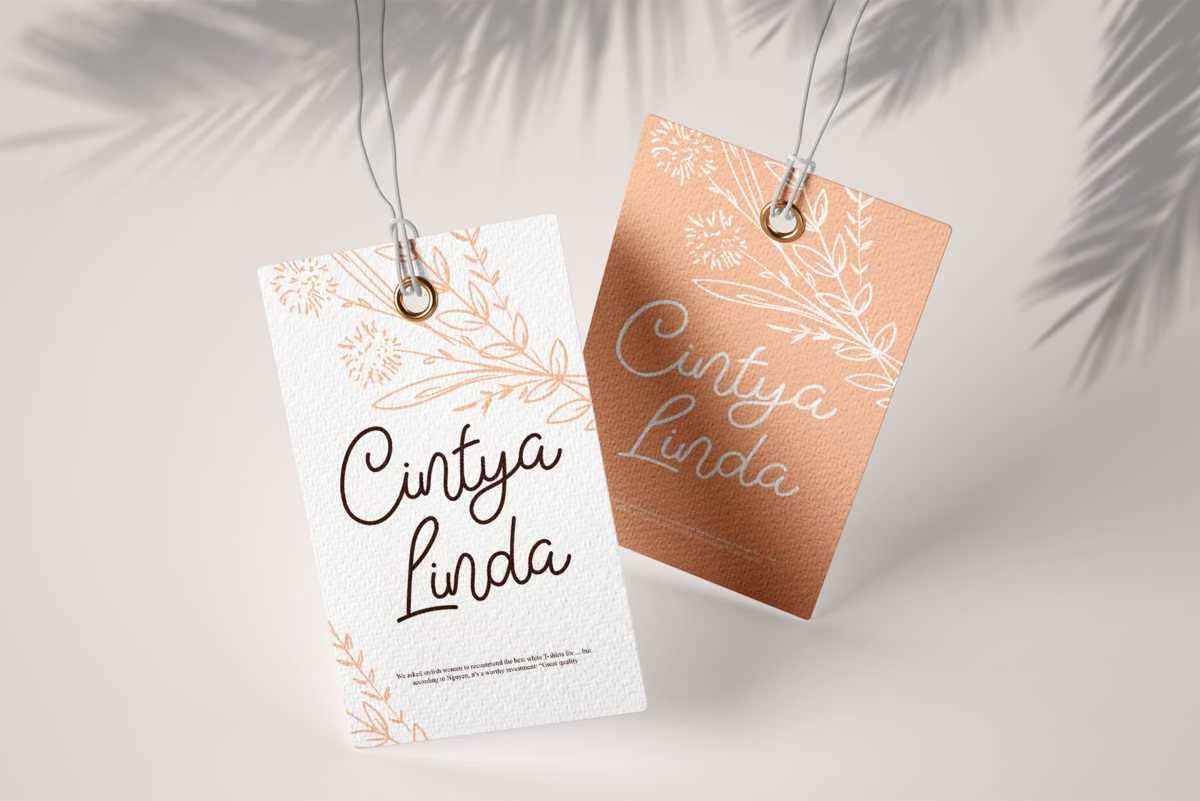
Astonia脚本字体。适合您的项目的文字和数字集合非常适合于徽标、品牌设计、徽标设计、数字刻字艺术、T恤/服装、海报、杂志、标志、广告设计和任何设计需求。Astonia脚本字体。适合您的项目的文字和数字集合非常适合于徽标、品牌设计、徽标设计,数字文字艺术、T恤/服装、海报、杂志、标志、广告设计和任何设计需求。